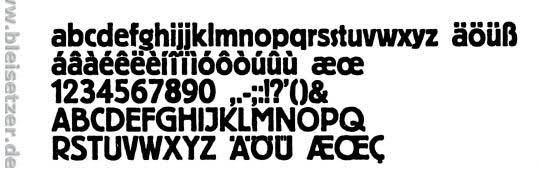
Erik Spiekermann hat ja auf der Typo 2010 gesagt das seine lieblingschrift die 'Block Reklameschrift' von Berthold ist. irgendwie dachte ich allerdings bei den bildern immer an die 'Berliner Grotesk' die Erik ja vor 30 jahren für Bertholds Fotosatz neugezeichnet hat.
und jetzt komm ich durcheinander, bei Myfonts wird die Berliner Grotesk in 3 garnituren mit diesem typischen kleinem g aufgelistet, die Block wird in den unterschiedlichen schnitten jedoch ohne diesem typischen g angeboten.
im Seemann ist die Block allerdings so abgebildet:
also wie die digitale Berliner Grotesk, ist das jetzt einfach in der digitalisierung untergegangen? zusätzlich gibt es noch eine Berliner Grotesk im Seeman, diese sieht so aus
ist die Berliner Grotesk, die wir digital kennen, eine neudigitalisierung (neuzeichnung) der Block? von wem ist die Berliner Grotesk damals gezeichnet wurden? bei GlobalType finde ich hinweise auf Hermann Hoffmann (Berthold), Poppelbaum und teilweise Louis Oppenheim (von dem ja die LoType ist, die nach einem ähnlichen prinzip gezeichnet wurde).
Im Bleisatz gabs die Berliner Grotesk (meines Wissens in zwei Schnitten mager und halbfett) von Berthold und die Block in mehreren Schnitten, die aber alle deutlich fetter waren als die halbfette Berliner Grotesk. Die Block gabs soweit ich weiß in den Schnitten normal, eng, schmal und kyrillisch und es gab auch eine sehr seltene Block hoch bzw. Hochblock (meines Wissens allerdings nicht von Berthold, sondern von einer Wiener Gießerei namens (ich glaube) Poppelbaum oder so). Die kursive Block ist meines Erachtens nach dem Bleisatz entstanden ...
Wie das kleine g aussah weiss ich nicht aus dem Kopf, sollte im Seemann richtig stehen. Vermutlich hat bei der Digitalisierung irgendein Ami mal wieder ein paar alte deutsche Schriftnamen durcheinander gewürfelt ...
Von der Block gab es folgende Garnituren, alle bei Berthold.
Block mager
Block Kursiv
Block halbfett
Block schwer
Block eng
Block schmal
Graublock
Hochblock
Die Block von Poppelbaum in Wien hieß zwar auch Block sah aber etwas anders aus.
Es gab dort 3 Varianten:
Block Kursiv
Block fett
Block licht
Das ist ein Scan von einem Andruck einer Original Berliner Grotesk halbfett von 1913. Die Qualität ist lausig. Nach dem Andruck ging der Schnitt zurück ins Blei.